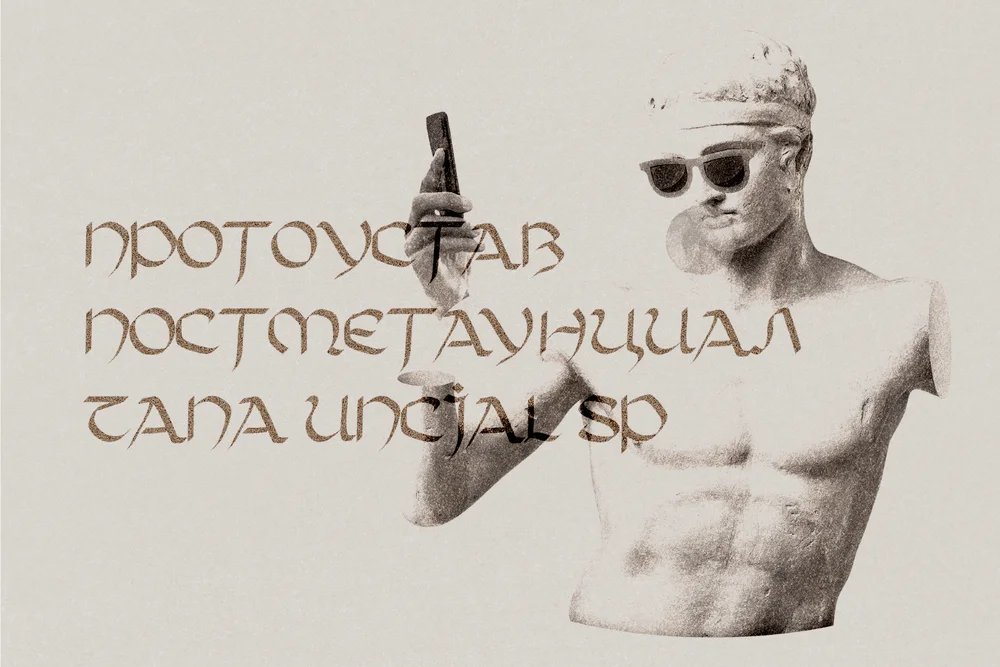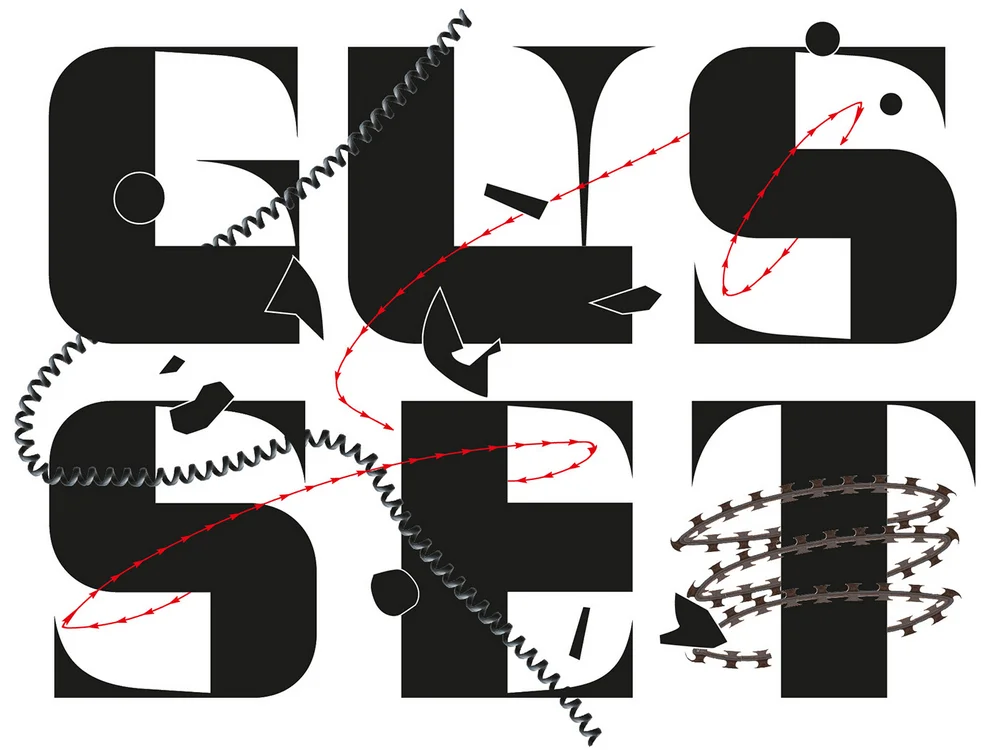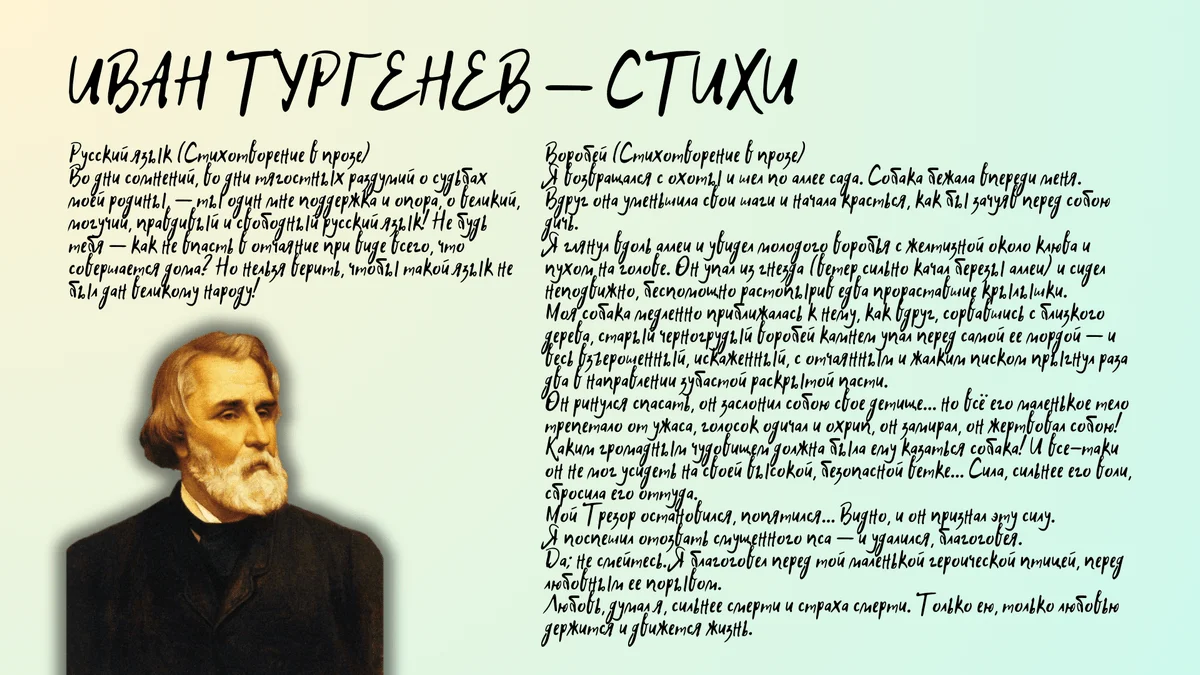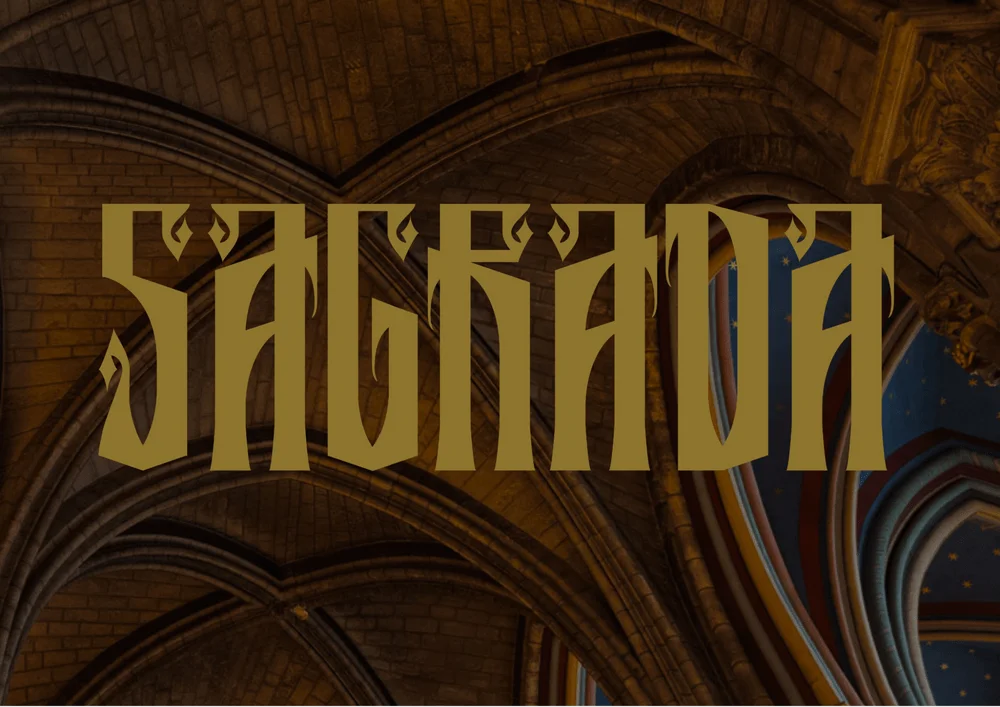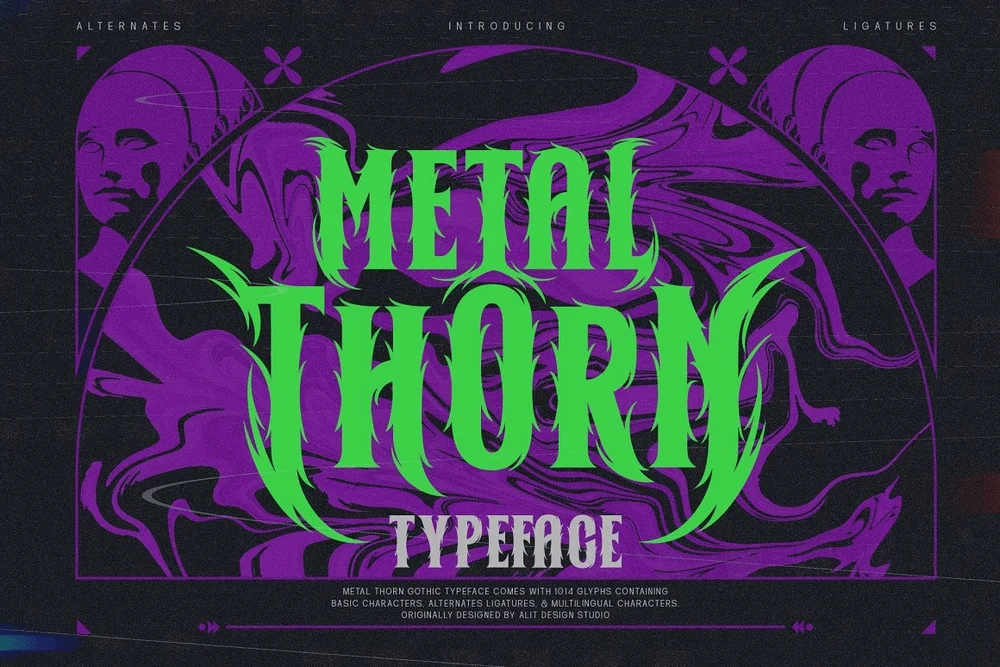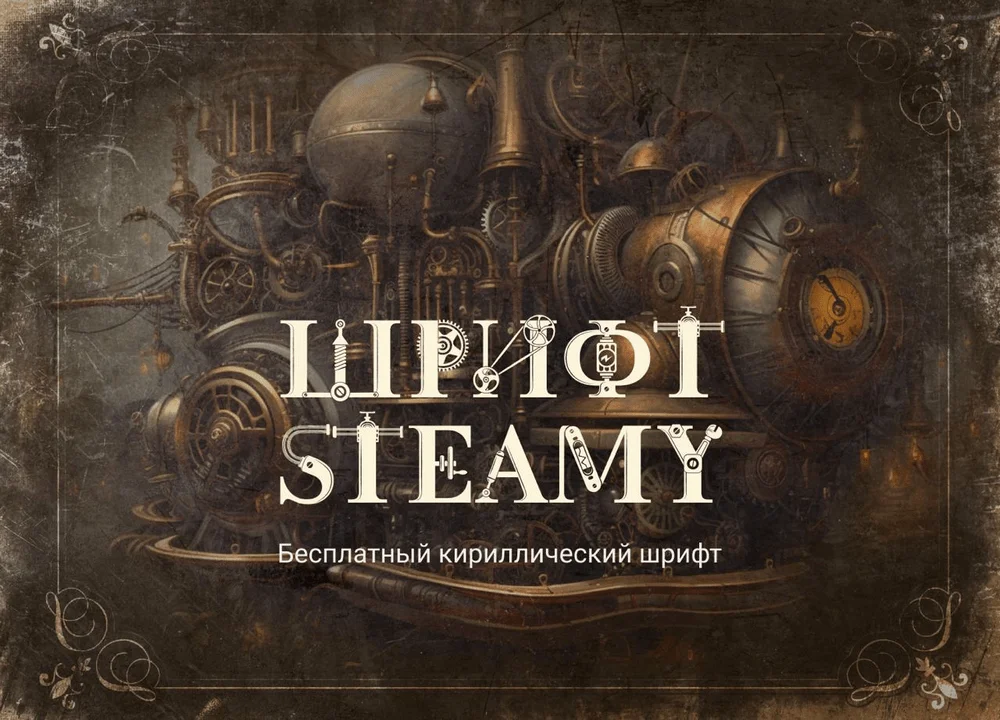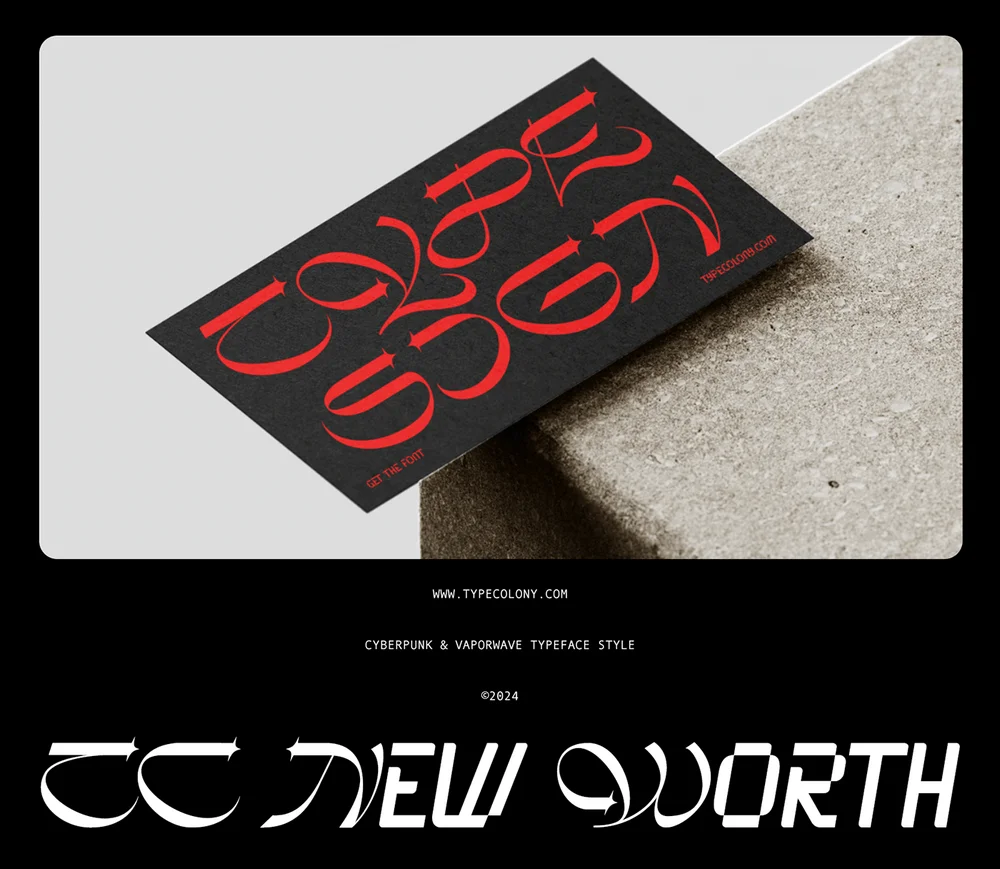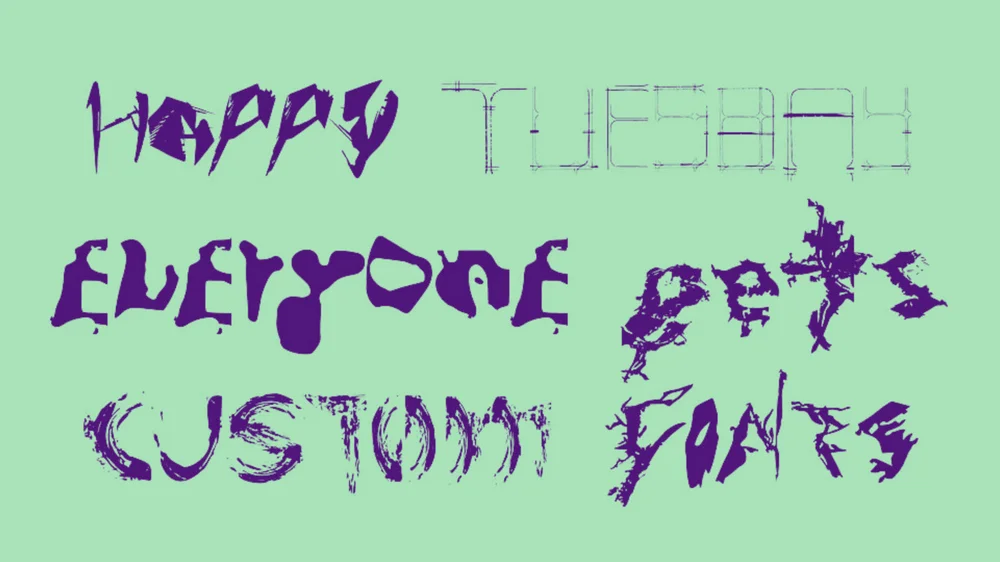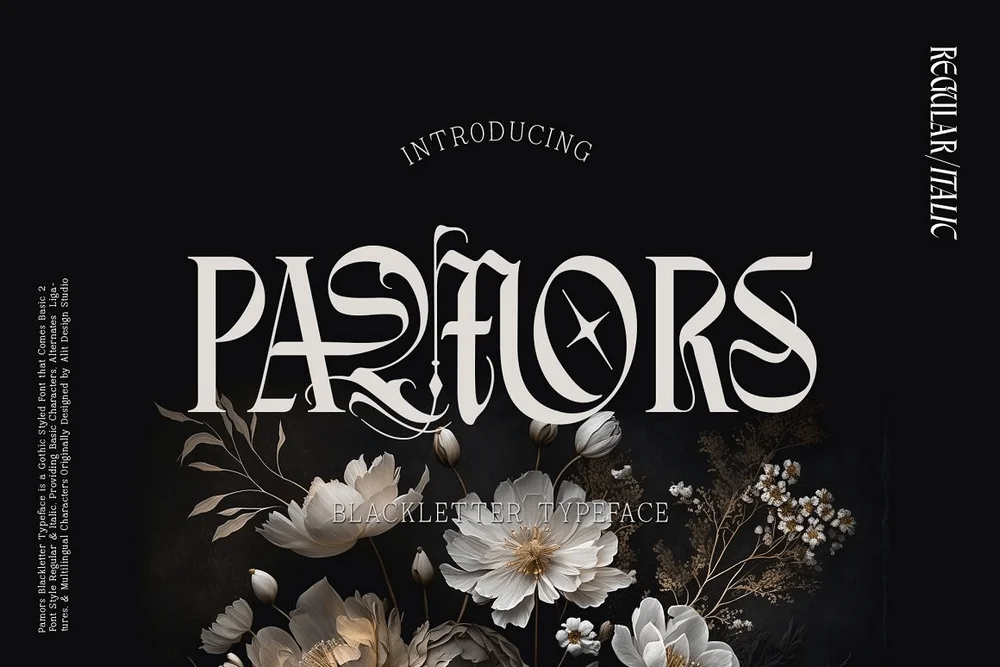
Для надписей в стиле стимпанка, Древней Греции или мультфильмов 1990-х годов
Обычно мы не задумываемся о шрифте при чтении текста. Но иногда шрифтовые дизайнеры выдают такой креатив, мимо которого трудно пройти мимо. Необычная пластика букв может подчеркнуть содержание текста, усилить эмоцию или просто привлечь внимание в потоке информационного шума. В статье расскажу про 15 бесплатных декоративных шрифтов, которые вызовут вау-эффект.
По словам автора, шрифт создан для нанесения ярких футуристических надписей на различные поверхности. Его визуальные особенности — строгие квадратные формы и линии под 45 градусов. У каждой буквы одинаковая высота и ширина, что создает ощущение гармонии и порядка. Hiper Ninja придаст современный стиль любому IT-проекту или технологическому стартапу. Его можно использовать в шрифтовом логотипе или на сайте.
В готическом шрифте есть удлиненные вертикальные линии и декоративные элементы, которые напоминают величественные своды и арки старинных соборов. У шрифта уникальный характер благодаря плавным изгибам и остроконечным деталям.
Sagrada подойдет, если в вашем дизайне нужен исторический или религиозный оттенок. Например, для титульных страниц книг, айдентики музейных выставок, афиш религиозных мероприятий и архитектурных презентаций.
В этом готическом шрифте есть острые, зазубренные края и плавные линии, которые напоминают шипы. Такой дизайн придает шрифту агрессивный вид. В нем сочетаются элементы классической готики с современными панк-рок деталями.
Metal Thorn идеально подходит для оформления афиш и обложек музыкальных альбомов, особенно в жанре метал. Он также уместен для использования в horror-тематике: например, для рекламы фестиваля фильмов ужасов или тематического квеста.
Steamy — шрифт, который вдохновлен эстетикой стимпанка. В его буквах сочетаются элементы механизмов, шестеренок и труб, что создает эффект индустриального дизайна XIX века. Каждый символ выглядит как часть сложного устройства.
Этот шрифт отлично подходит для заголовков на сайтах, которые посвящены технологиям, играм и фантастике. Он будет уместен в оформлении квестов, афиш для мероприятий в стиле стимпанк, брендинга игр, мероприятий и мастер-классов.
В шрифте есть нотки киберпанка. У букв футуристические формы с плавными линиями и острыми углами. Контуры символов напоминают технологические узоры и неоновые вывески, что придает надписям современный вид. TC New Worth будет уместен на сайте дизайн-студии или в названии лимитированной коллекции одежды онлайн-бутика.
Это семейство шрифтов сочетает в себе множество текстур, которые придают дизайну «тактильное» измерение. По словам автора, буквы тщательно подобраны друг к другу и создают многогранный визуальный опыт. Необычные формы символов делают шрифт идеальным для привлечения внимания, а среди многообразия начертаний можно выбрать вариант под любое настроение. Urging Osmosis в логотипах и фирменном стиле сделает бренд выделяющимся. Но в качестве шрифтовой пары точно стоит подобрать что-нибудь более спокойное.
Это Google-шрифт, который наполнен энергией и игривостью. В нем есть нестандартные формы, отсылающие к мультфильмам 1990-х годов. Буквы украшены точками, линиями и завитками. Шрифт отлично передает ощущение беззаботности и привлекает внимание своими веселыми формами.
Kablammo будет хорошо смотреться в детских книгах и комиксах. Он уместен в дизайне упаковки для игрушек и других продуктов, которые ориентированы на детей. Шрифт также можно использовать в рекламе, если нужно создать атмосферу радости и развлечения.
Шрифт отличается своими плавными формами и визуальным эффектом текучести. Его буквы выглядят так, будто они сделаны из геля. Он привлекает внимание смелым дизайном, хотя разобрать слова с первого прочтения может быть непросто.
Yunga будет уместен в дизайне афиш и плакатов для музыкальных фестивалей, художественных выставок и других прогрессивных мероприятий. Также шрифт отлично подойдет для креативного брендинга, рекламы модных и технологических продуктов.
Шрифт в готическом стиле выделяется элегантностью и изяществом. У него сложные изгибы, декоративные элементы и плавные переходы, что придает буквам уникальность и утонченность. Pamors сочетает в себе традиционные готические формы с современными дизайнерскими акцентами.
А если использовать декоративные шрифты для длинных текстов, выйдет что-то такое. Читать практически невозможно.
Используйте нестандартные шрифты для акцентов в дизайне, но не слишком увлекайтесь. В любой непонятной ситуации попросите знакомых взглянуть на макет. Если важную информацию им не удается уловить в первые секунды, вероятно, типографика должна быть более простой. В нашей подборке шрифтов для заголовков можно найти броские, но сдержанные варианты, с которыми точно не промахнетесь.